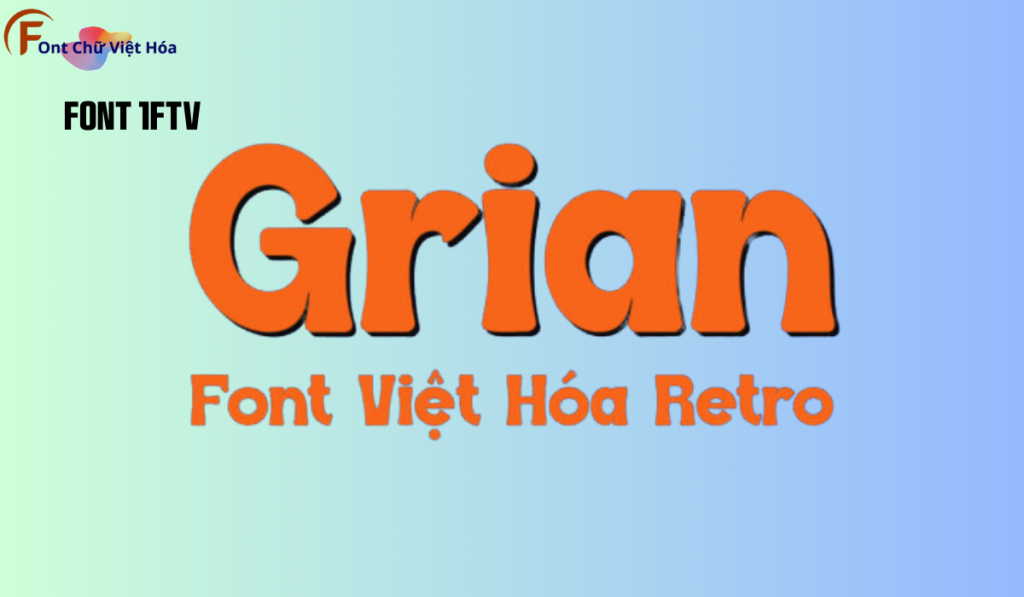
Font 1FTV Grian
Font 1FTV Grian là một font chữ độc đáo, thuộc bộ 1FTV, nổi bật với phong cách sans-serif hiện đại và các đường nét mềm mại, tinh tế. Thiết kế của 1FTV Grian tập trung vào sự thanh lịch và dễ đọc, đặc biệt phù hợp cho các thiết kế đòi hỏi tính thẩm mỹ cao như poster, logo, và tiêu đề. Với tỷ lệ chữ cân đối và các đường nét rõ ràng, font này tạo ra ấn tượng thị giác mạnh mẽ và giúp tối ưu hóa không gian trong thiết kế. Font này cũng đã được Việt hóa, mang đến sự linh hoạt và tiện dụng cho các dự án thiết kế bằng tiếng Việt.